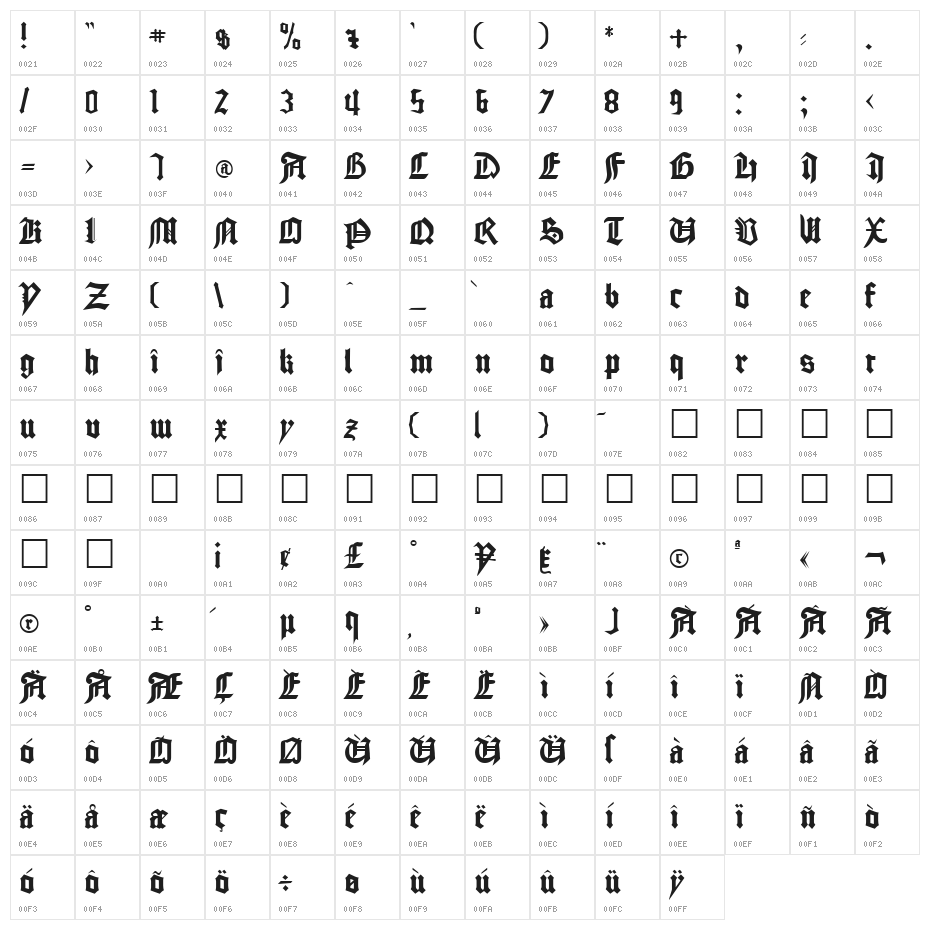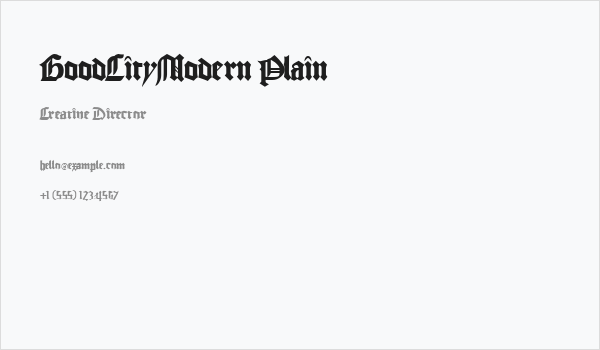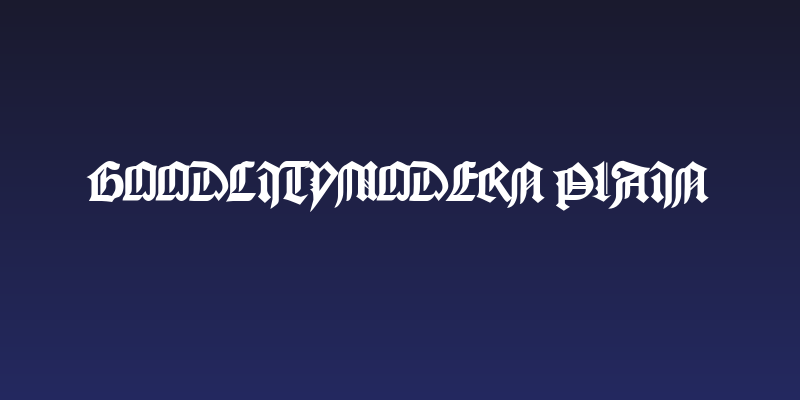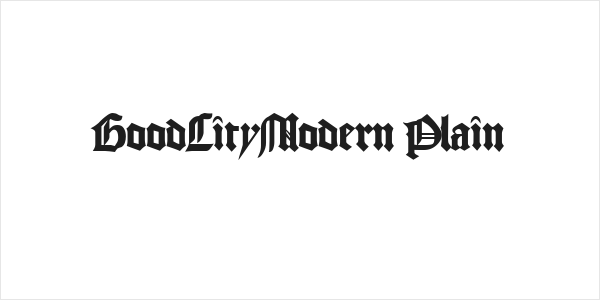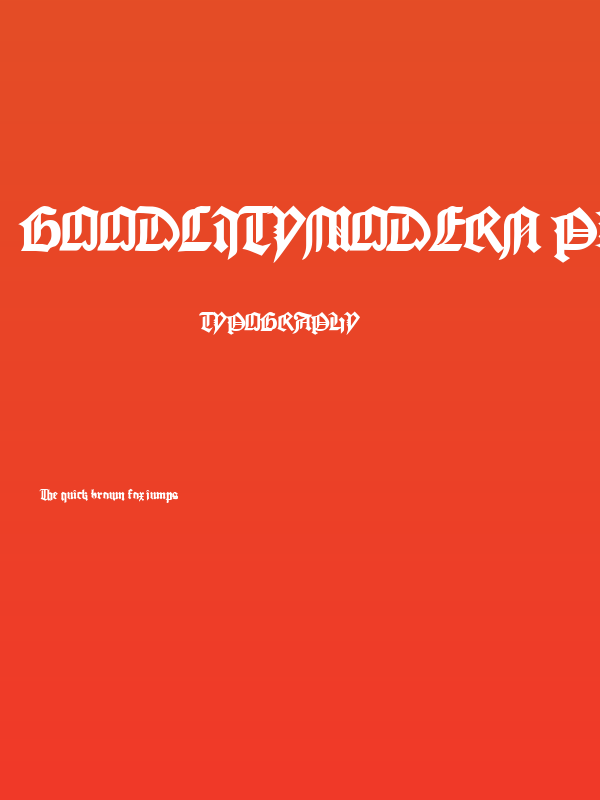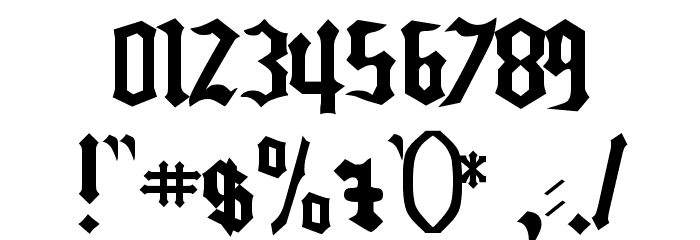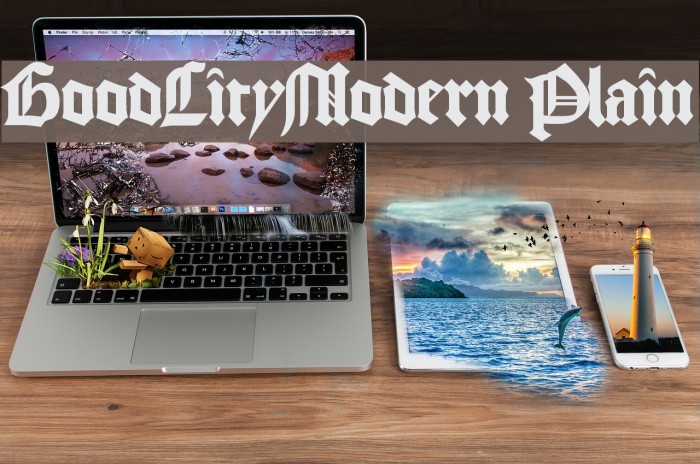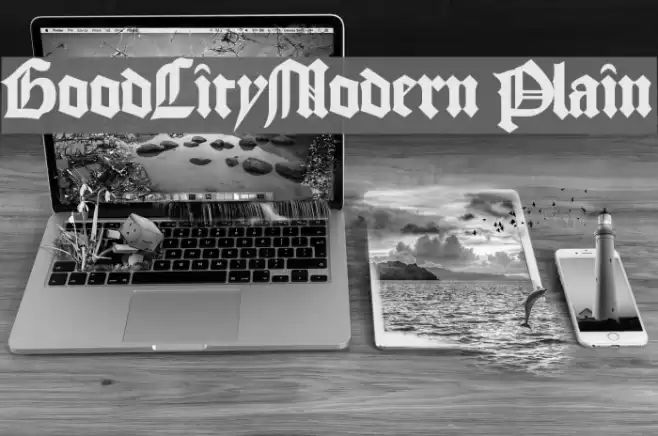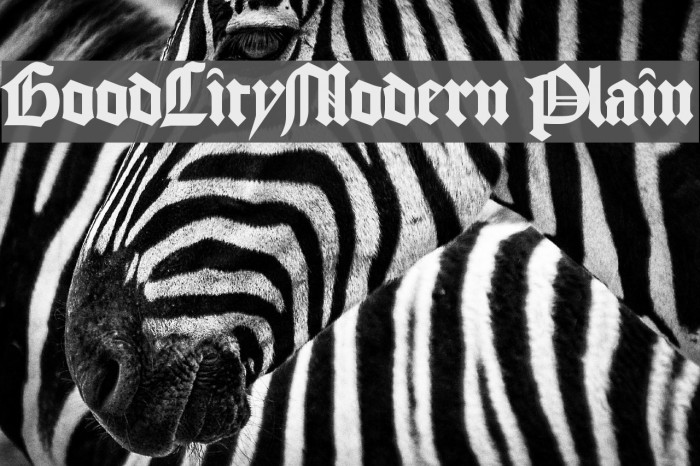
GoodCityModern Plain Font
| 分类 | Gothic |
| 整体风格 | Vintage |
| 推荐项目 | Ideal for projects requiring a dramatic and historical feel, such as event posters, book covers, or branding for vintage-themed products. |